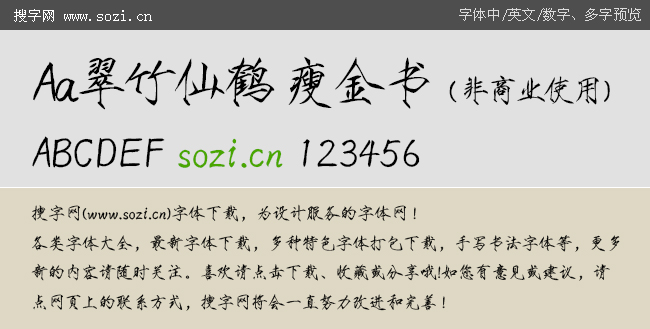
Aa翠竹仙鶴瘦金書
搜字網(wǎng)給大家提供一款A(yù)a翠竹仙鶴瘦金書(非商業(yè)使用)中文字體下載,Aa翠竹仙鶴瘦金書是一款手寫書法字體,字體運(yùn)筆直如矢、勁如鐵,結(jié)體縱伸橫逸,狹瘦勁挺。適合應(yīng)用于藝術(shù)設(shè)計(jì)、平面宣傳設(shè)計(jì)、網(wǎng)頁設(shè)計(jì)、海報(bào)設(shè)計(jì)等應(yīng)用(此字體為個(gè)人非商用版,商用可以聯(lián)系QQ:1006760504)。